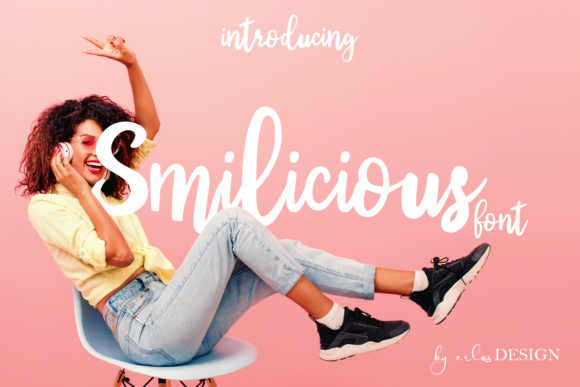
Creativefabrica Smilicious Font
[Creativefabrica] Smilicious Font
Smilicious - это современный каллиграфический шрифт, с плавной линией, танцевальной основой и элегантным прикосновением. Его можно использовать для различных целей, таких как заголовки, логотипы, приглашение на день рождения, футболка, фирменный бланк, плакаты и многое другое.